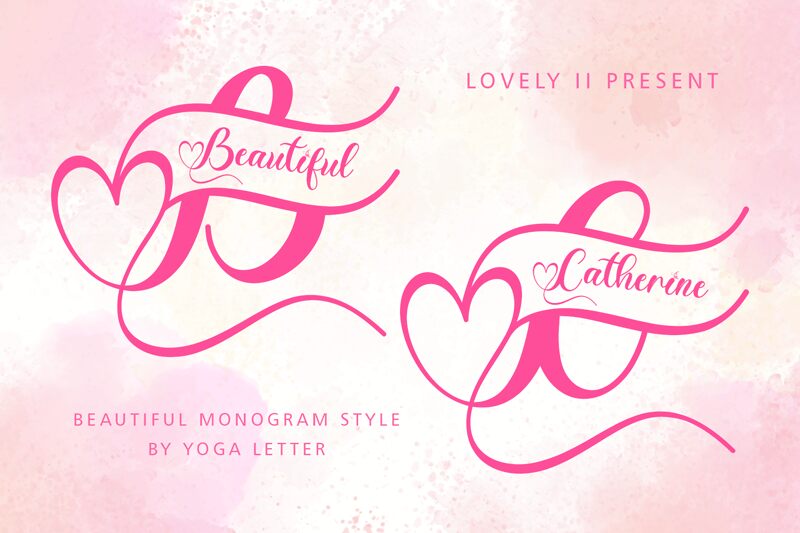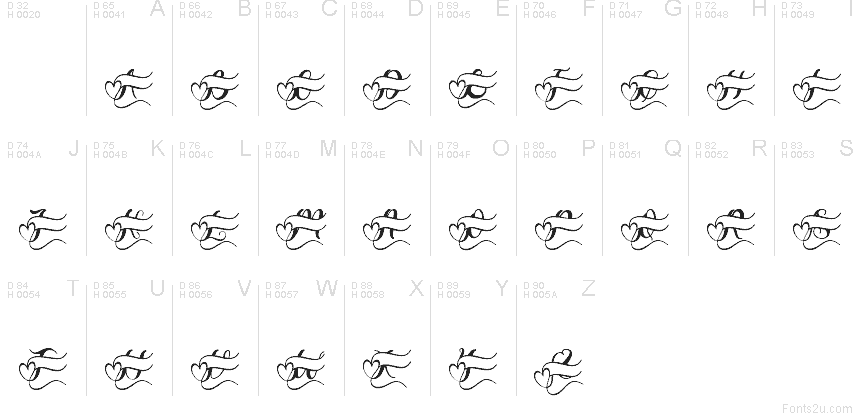
Catherine Monogram Style
Catherine Monogram Style de Yoga Letter es una tipografía de monogramas gratuita ideal para San Valentín, con líneas de escritura entrelazadas y un detalle en forma de corazón que recorre todo el diseño. Sus trazos fluidos se curvan en amplias florituras en lugar de formar letras convencionales, aportándole un aire ornamental dibujado a mano, perfecto para decoraciones románticas.
Catherine Monogram Style funciona de maravilla en invitaciones de boda, tarjetas de San Valentín, etiquetas de regalo, logotipos de monogramas y diseños decorativos donde un motivo de corazón suave aporte armonía al conjunto. Esta fuente gratuita también es perfecta para títulos de álbumes de recortes, branding de boutiques y papelería, ya que sus líneas elegantes se leen como un emblema único más que como texto corriente.